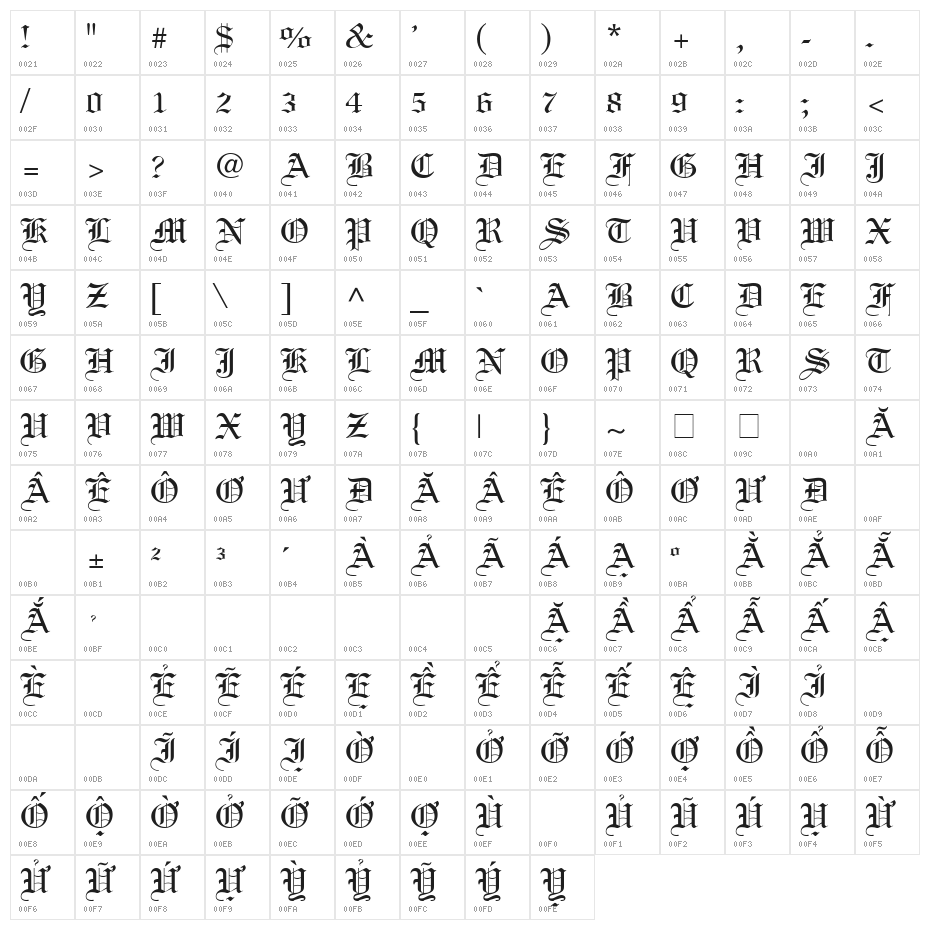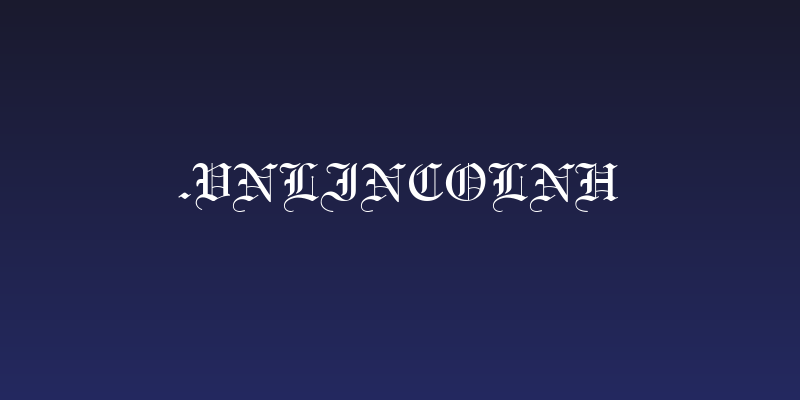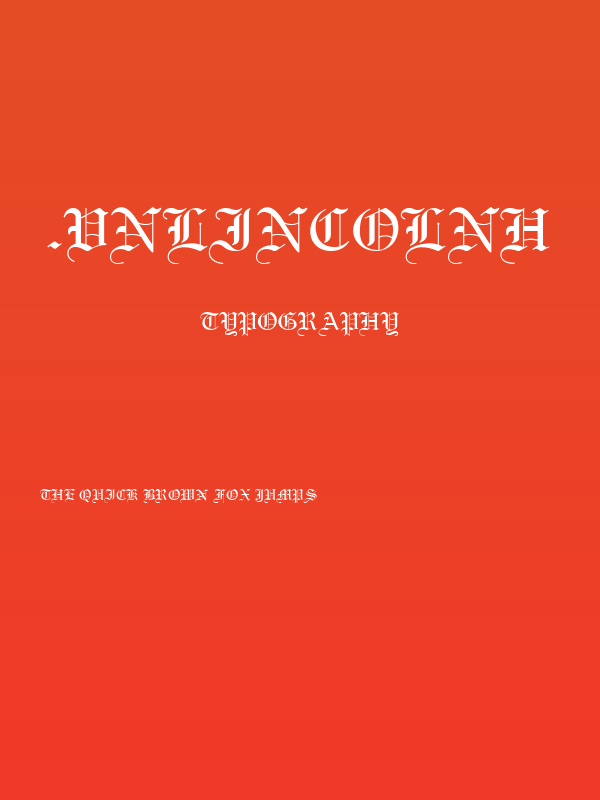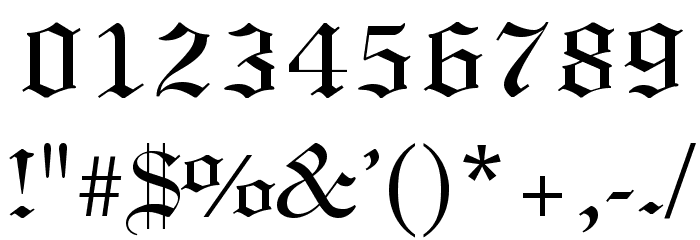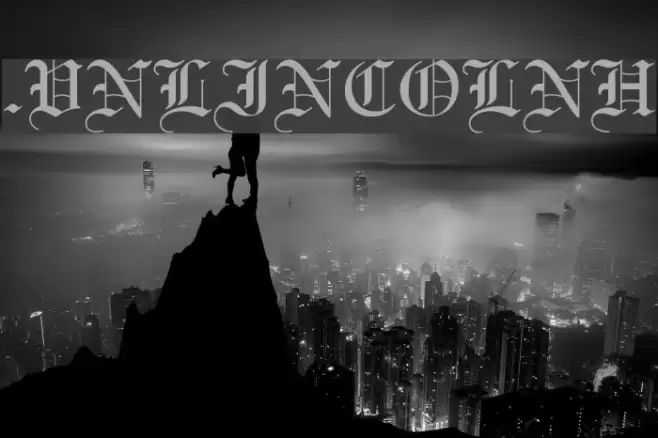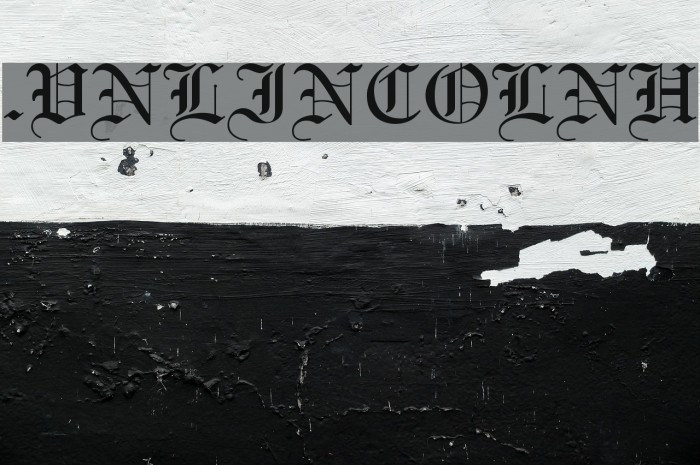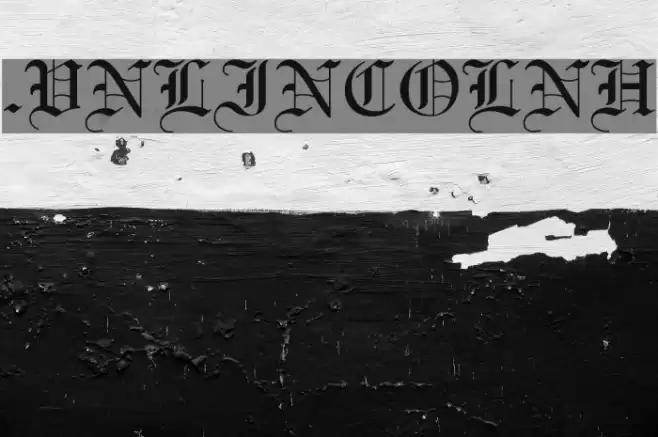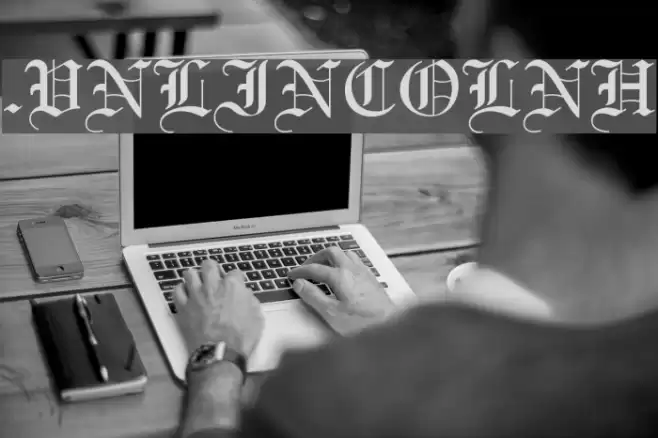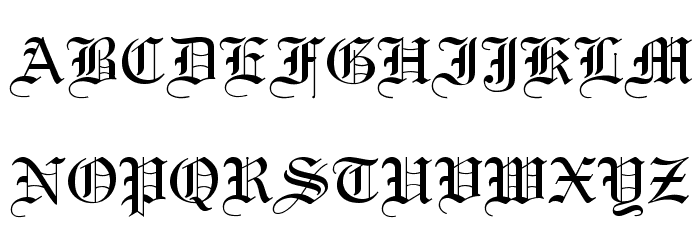
.VnLincolnH Font
| Categorie | Gothic |
| Progetti proposti | Ideal for historical documents, wedding invitations, book covers, and branding that requires a traditional or gothic touch. |